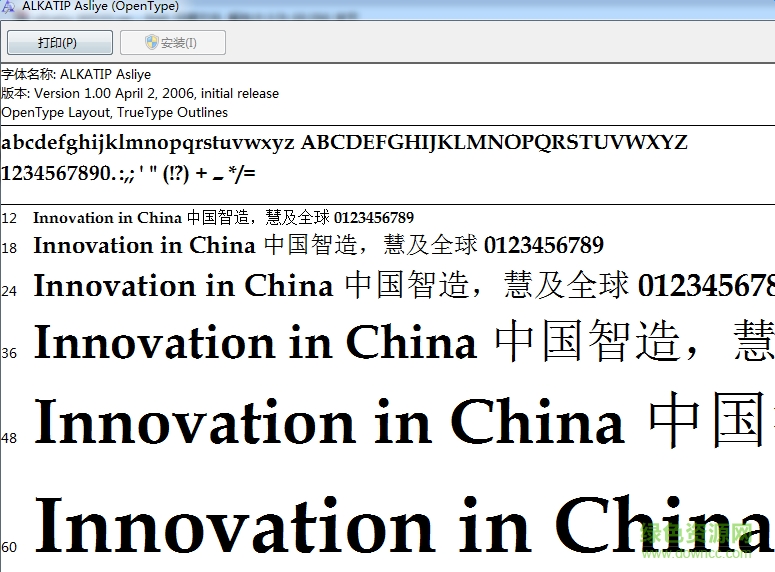
alkatip字體,全稱alkatip asliye,是一款英文字體庫中的個性字體,能夠適用于產(chǎn)品包裝、電視臺廣告、電影、電視劇片頭以及內(nèi)容用字等領(lǐng)域,喜歡的網(wǎng)友可免費(fèi)下載收藏。
alkatip asliye字體是英文字體庫中極具個性的一款字體,該字體的線條粗細(xì)適中,自行非常端莊大方,有喜歡的朋友趕快來綠色資源網(wǎng)下載使用吧!